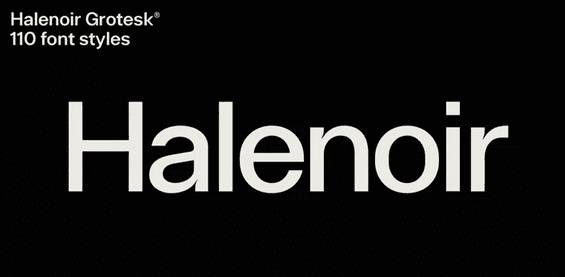
Название: Halenoir Font (2021)
Halenoir - это современный шрифт sans serif с геометрическим оттенком, поддерживающий 28 языков. Он поставляется в 10 весах, 102 верхах и соответствующих им начертаниях, Obliques, pattern, так что вы можете использовать их по своему усмотрению, в каждом из которых более 801+ глифов.
Халенуар состоит из 3 типов: Original, Compact, Expanded, и каждый из них разработан таким образом, чтобы подходить для мобильного, графического и редакционного дизайна.
Halenoir включает 102 шрифта, состоящих из трех различных оптических размеров: Display и Text. Каждый из них был тщательно адаптирован к требованиям своего размера. Более крупные версии Display нарисованы так, чтобы продемонстрировать тонкость Halenoir и расставлены с учетом заголовков, в то время как размеры Text сфокусированы на разборчивости, используя четкие штрихи и комфортно свободные пространства. Каждый вес шрифта включает в себя расширенную языковую поддержку, дроби, табличные фигуры, стрелки, лигатуры и многое другое.